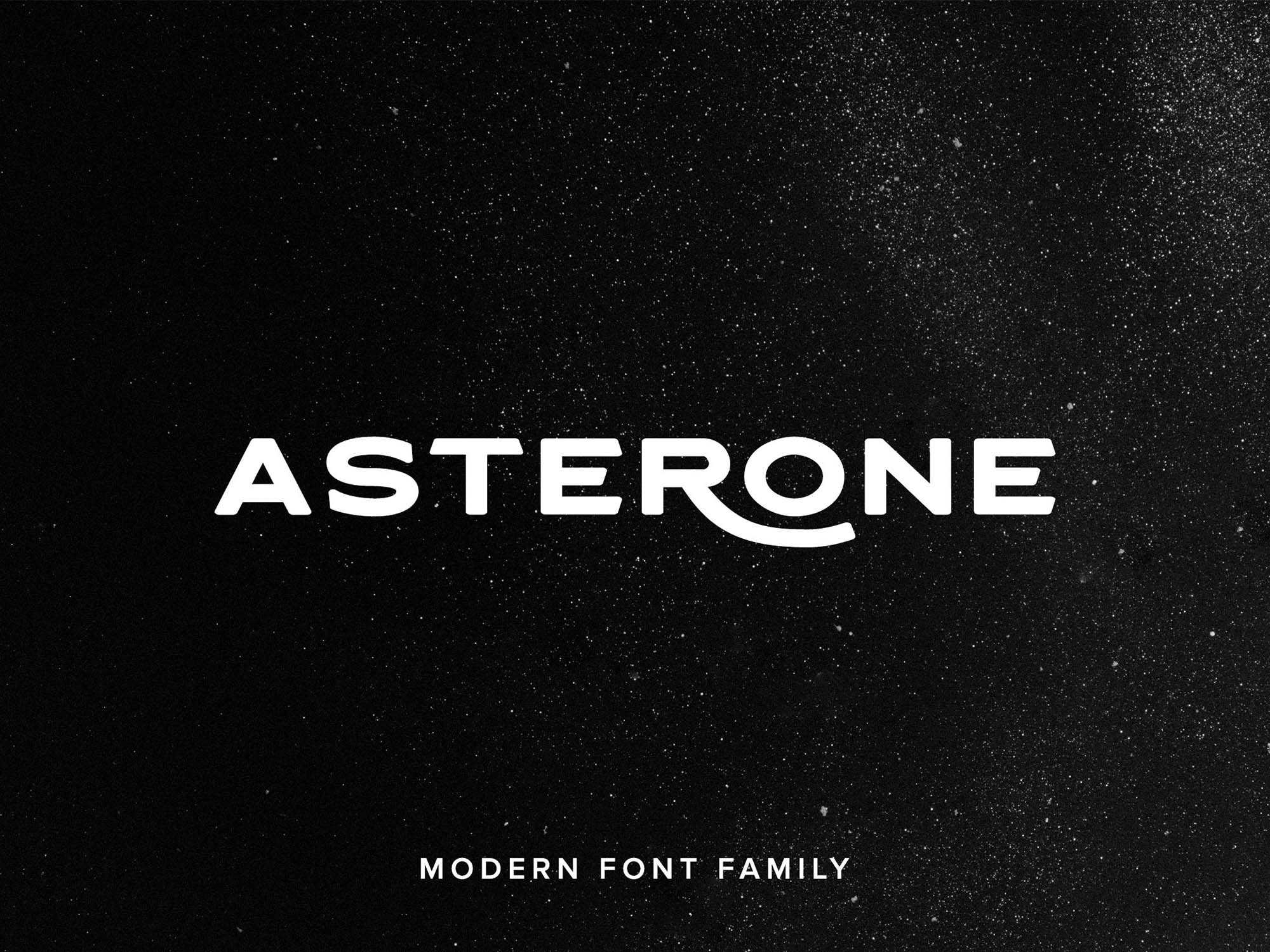
Asterone Font Family – Download Grátis
Asterone Font Family é uma família de fontes que inspira seus admiradores na atmosfera mística do cosmos. Essa fonte, em sua complexidade e diversidade, parece transportar os espectadores para além dos céus noturnos, onde estrelas dançam em harmonia. De uma forma poderosa e autônoma, a família de fontes representa a infinita vastidão das estrelas e do universo. Embora muitas vezes nos esforçemos para fazer comparações, é difícil negar a capacidade das fontes, particularmente esta, de criar algo que atraia e fascina os olhos do mundo, simplesmente por sua beleza e originalidade. Ao ver Asterone, você é transportado para um universo de imaginação onde letras e estrelas se unem em uma poesia visual.